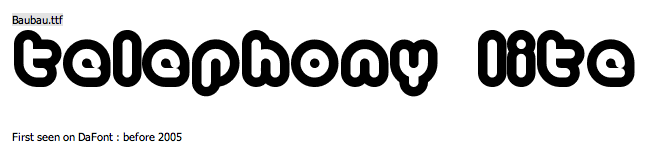
Ich finde die Schriftart nirgendwo, hat jemand eine Idee?
sieht handgemacht aus.
hier gibt es eine Grundlage (die Quelle darf man hier ja nicht verlinken):